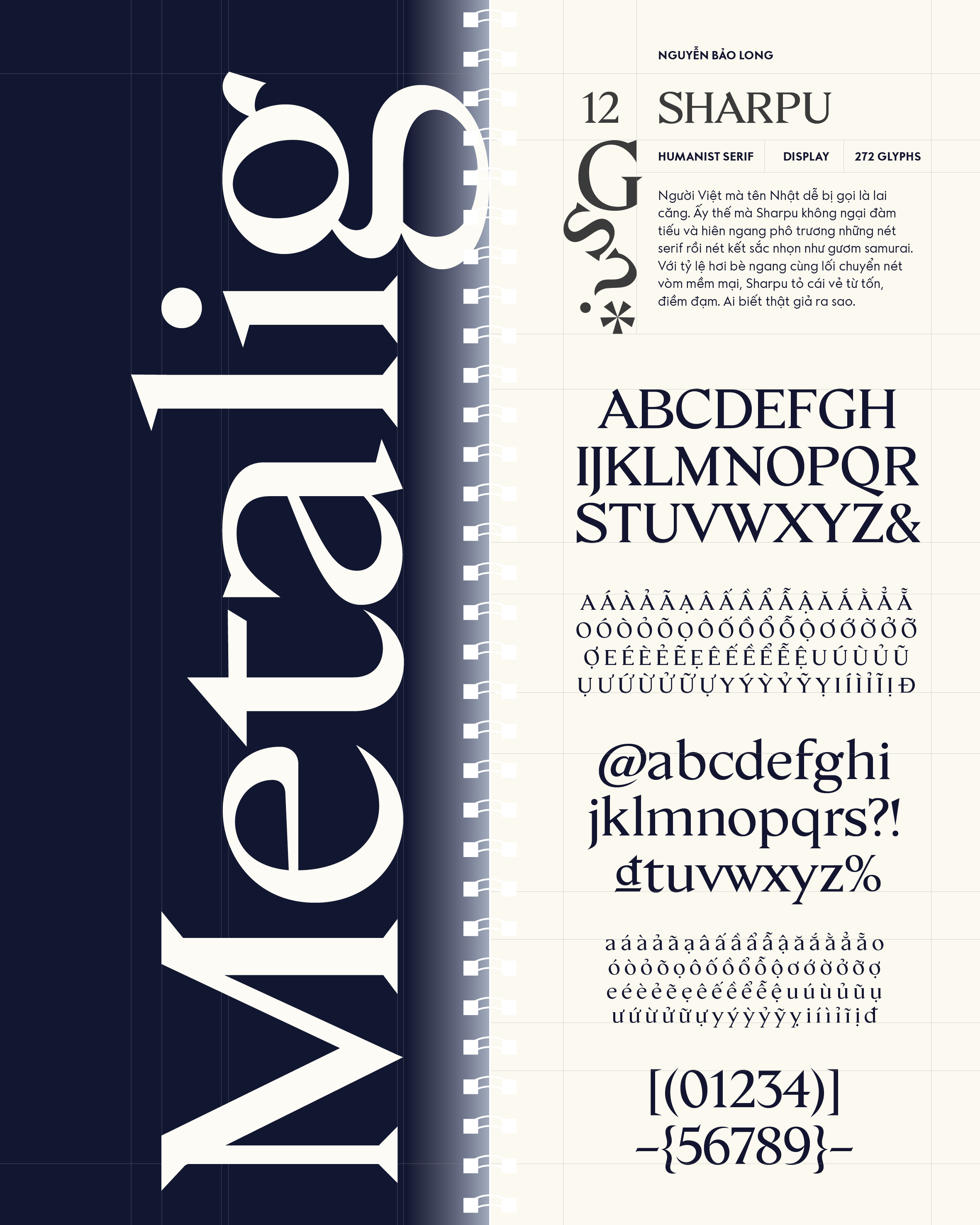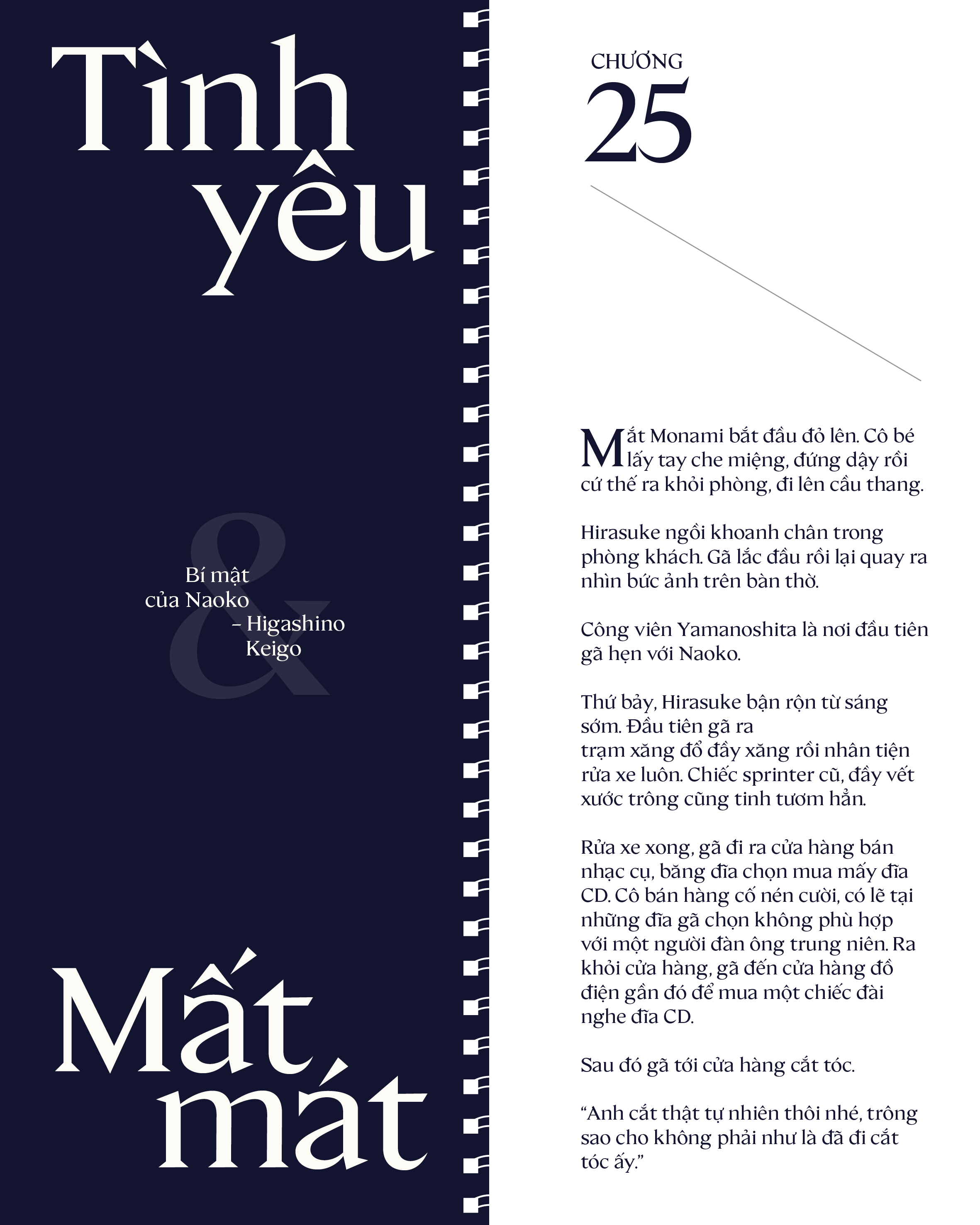
Sharpu
Về Sharpu: Người Việt mà tên Nhật dễ bị gọi là lai căng. Ấy thế mà Sharpu không ngại đàm tiếu và hiên ngang phô trương những nét serif rồi nét kết sắc nhọn như gươm samurai. Với tỷ lệ hơi bè ngang cùng lối chuyển nét vòm mềm mại, Sharpu tỏ cái vẻ từ tốn, điềm đạm. Ai biết thật giả ra sao.
Humanist Serif
Display
Nguyễn Bảo Long